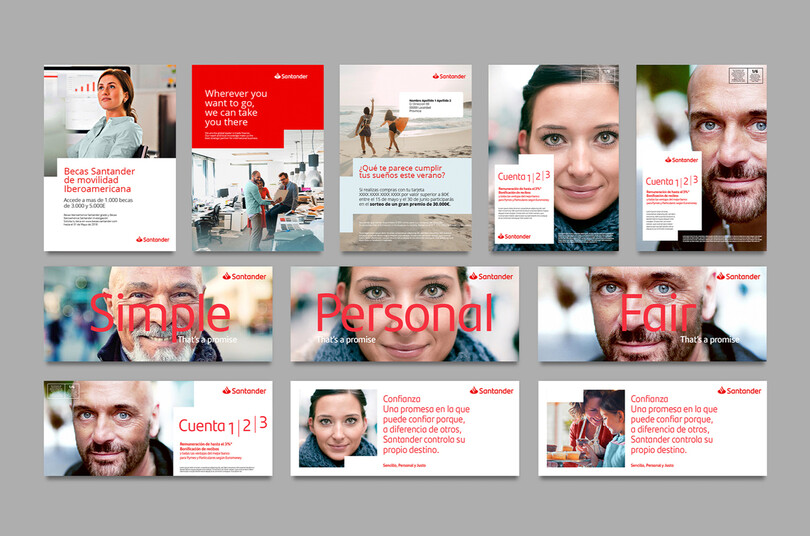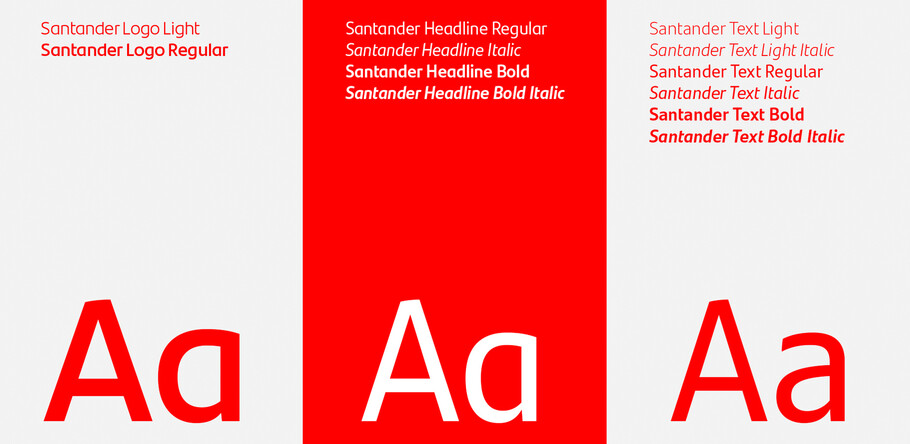
Konsistente Identität für eine wegweisende Bankengruppe.
Monotype entwarf eine Schrift, die von jeder Abteilung bei Santander ohne nachträgliche Anpassungen oder komplizierte Anleitungen sofort zu benutzen ist.
So stattete sich Santander neu aus, um mit seinen Kunden authentisch, lesbar und klar auf allen Kanälen zu kommunizieren.
Die Herausforderung.
Seit drei Jahrzehnten wächst Santander weltweit. Obwohl die Bank für ihre europäischen Aktivitäten bekannt ist, hat sie ihr Business vor allem auf den amerikanischen Kontinenten ausgeweitet. Durch Akquisitionen, den Einstieg in neue Märkte plus einer wachsenden Produktpalette geriet die Marke Santander zunehmend unter Druck, ihr Erscheinungsbild innerhalb der Bankengruppe zu erhalten. Darüber hinaus begegneten dem Unternehmen einschneidende Marktveränderungen:
• die digitale Transformation und der Trend zu neuen Kanälen in der Markenkommunikation
• eine neue Wahrnehmung von Marken im Allgemeinender und bei den jungen Verbrauchern vor allem im Bankensektor
• das Bedürfnis, eine relevante und konsistente Erfahrung zu liefern, die die Kunden vor Ort einbindet und gleichzeitig das gesamte globale Portfolio aufeinander abstimmt
Im Rahmen der Marken-Neugestaltung wurde schnell klar, dass Santander eine stimmigere und zukunftsorientierte Schrift-Strategie entwickeln muss. Als Interbrand und Monotype sich zu Beginn darüber austauschten, eine exklusive Schriftfamilie für Santander zu entwickeln, hatte die Marke vier Schriften für verschiedene Zwecke im Einsatz: FF Kievit, Berling, Open Sans und Arial.
Die Lösung.
Am Beginn der Kooperation von Santander, Interbrand und Monotype stand die Neukonzeption der Wortmarke und der Submarken-Architektur. Viele Logos bediente sich Elemente klassischer Schriften wie Times, Century, Berling, Garamond und Bodoni, die sie ziemlichveraltet aussehen ließen. Santander und seine Partner wollten eine Identität jenseits von Farben und Bildzeichen definieren, und zwar eine, die sofort wiedererkennbar und im Einklang mit der Positionierung „echter Wohlstand, jeden Tag“ und den Werten „einfach, persönlich und gerecht“ stehen sollte.
�Wir mussten eine Schrift entwickeln, die sowohl im Druck als auch digital funktioniert, eine überschaubare Anzahl von Schnitten bietet und über alle Kontinente einsetzbar ist.
— Borja Borrero, geschäftsführender Kreativdirektor, Interbrand.
Logo-Redesign: zwei Optionen.
Vor der Entwicklung des Logo-Fonts wurden bereits verschiedene Buchstaben-Eigenschaften in Marken-Workshops entwickelt, die übernommen werden sollten, z. B. der geschlossene Kleinbuchstabe e, das t mit halbiertem Querbalken sowie die Lettern n und r ohne Sporn. Mit diesen Vorgaben konnte sich Hendrik Weber vom Monotype Studio ganz auf die Konzeption der Gesamtfamilie fokussieren. Er bot zwei stilistische Richtungen an: als erstes eine eher humanistische Anmutung mit „weichen“ Buchstaben und einer starken Persönlichkeit, sowie eine „sportlichere“ bzw. „modulierte“ Alternative, die statisch und zeitlos war. Santander und Interbrand entschieden sich für das erste Konzept, den humanistischen Ansatz.
Feinheiten und Logo-Font.
Um die Markenarchitektur von Santander neu zu entwickeln, wurde zunächst ein komplettes Alphabet entwickelt, das auf den sieben Glyphen der Wortmarke (S,a,n,t,a,n,d,e,r) basiert. Der daraus hergeleitete Logo-Font beinhaltete den kompletten Latin-Zeichensatz und die beiden Strichstärken Regular und Light. Die Flamme im Logo wurde optimiert und vereinfacht, um perfekt mit den Glyphen der Wortmarke zu harmonieren; dabei half ein Raster, das für abstandsgleiche Linien, Innenräume und gleichmäßige Winkel sorgte. Die Flamme wurde in den Zeichensatz integriert, um sowohl einen einfachen Zugang als auch das Bildzeichen-Buchstaben-Zusammenspiel sicherzustellen (Größe, Grauwert, Abstand).
Die Notwendigkeit einer Hausschrift.
Nachdem das Logo und der Logo-Font entwickelt waren, wurde schnell klar, dass die Marke Santander ihr Identitätssystem erweitern muss, um die visuelle Stimme ihrer Marke über alle Kanäle – digital und Print – klar zu transportieren. Für Hendrik Weber war die erste Etappe dieses Prozesses die Entwicklung einer Schrift für Texte und Headlines, die sich an die Glyphen des Logos anlehnt, aber für Lesetexte optimiert ist. Er vergrößerte die Mittellänge, sowie Oberlängen und Unterlängen und natürlich die Laufweite. Er fertigte auch Entwürfe für alternative Kleinbuchstaben an, zum Beispiel g und a, die sich auf Antiqua-Formen stützten. Von da an fanden regelmäßige Workshops zwischen Monotype, Interbrand und Santander statt, in denen weitere Alternativzeichen und andere Eigenschaften der Schriftfamilie diskutiert wurden..
So entstanden weitere Feinheiten für die Textschrift: die Kleinbuchstaben i, j und l mit Fuß, b, m, n und r mit Sporn sowie die Lettern f und t mit komplettem Querbalken.
Damit das Identitätssystem über alle Kanäle, Regionen und Untermarken von Santander funktionieren konnte, empfahlen Interbrand und Monotype eine dichte optische Verwandtschaft zwischen Wortmarke und Hausschrift. Vor allem sollten Überschriften und Titelsatz die gleichen Merkmale wie der Logofont aufweisen. Die enge Zurichtung und die Form der Buchstaben waren hier besonders wichtig. Schließlich wurde auch eine Micro-Version für Kleingedrucktes in die Planung mit aufgenommen, um die Lesbarkeit an Kleinbildschirmen sowie die von Verträgen und Fußnoten zu verbessern.
• die Fähigkeit mit einer starken, koordinierten Stimme an jedem Kunden-Touchpoint zu kommunizieren
Extern:
• im Zusammenspiel mit dem Rebranding unterstützt die Exklusivschrift die neue visuelle Identität von Santander
• eine Schrift, die in aufstrebenden und traditionellen Kanälen sowie in allen Regionen der Welt funktioniert und damit für Expansion ausgelegt ist
• ein konsistentes Markenerlebnis, das in wichtigen Verbrauchersegmenten warmherzig und vertrauenerweckend wirkt